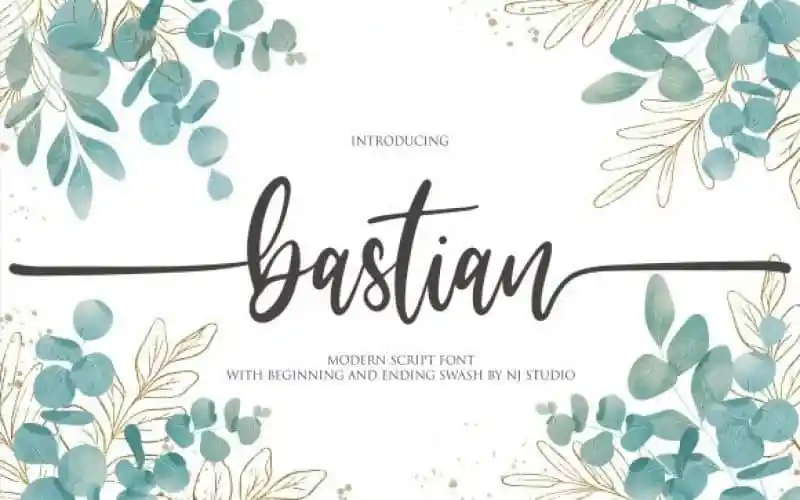
Bastian Calligraphy Font – Download Grátis
A Bastian Calligraphy Font é inspirada no estilo moderno de escrita cursiva, fornecendo uma temática divertida que se destaca perfeitamente para projetos de exibição, design de camisetas, trabalhos manuais, assinaturas de citações e logotipos. Ela traz um toque de luxo a qualquer projeto gráfico que você desejasse criar. Esta fonte não só é versátil como também enriquece seus projetos digitais com uma personalidade única e encantadora. Sua elegância e sofisticação se combinam perfeitamente com o modernismo do estilo da escrita cursiva, tornando-a um recurso indispensável para designers em busca de dar um toque especial às suas criações.